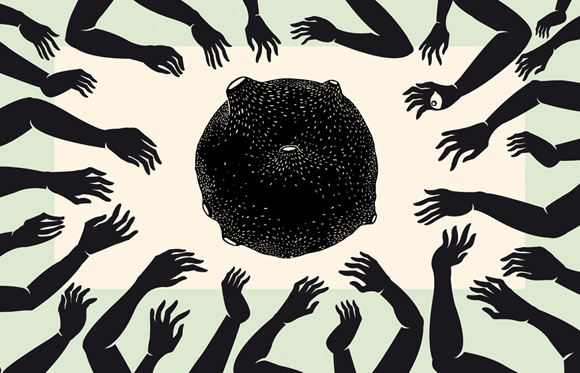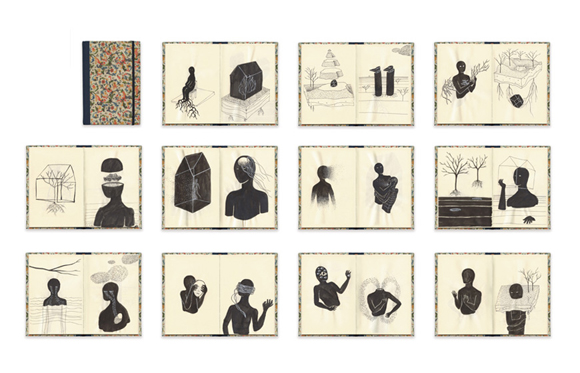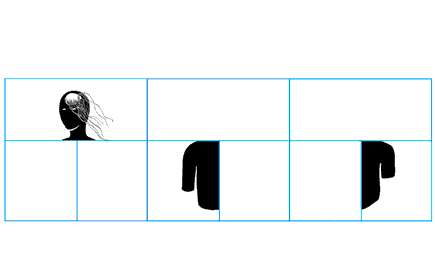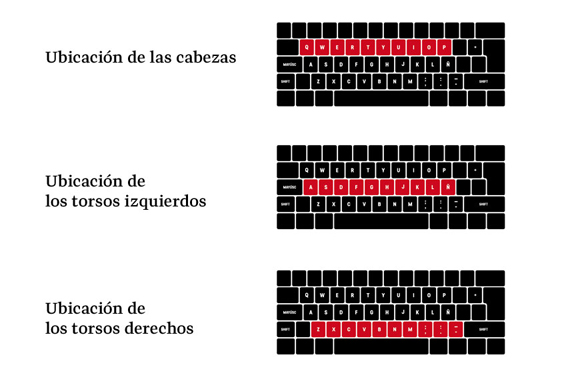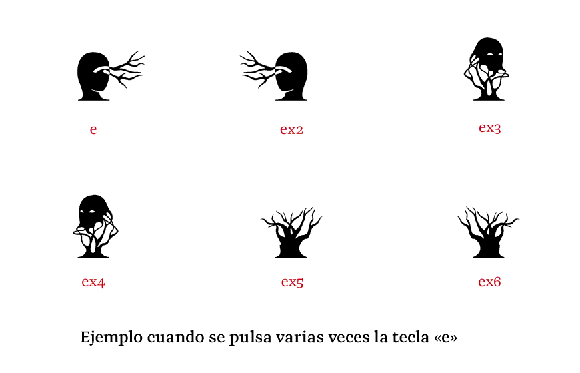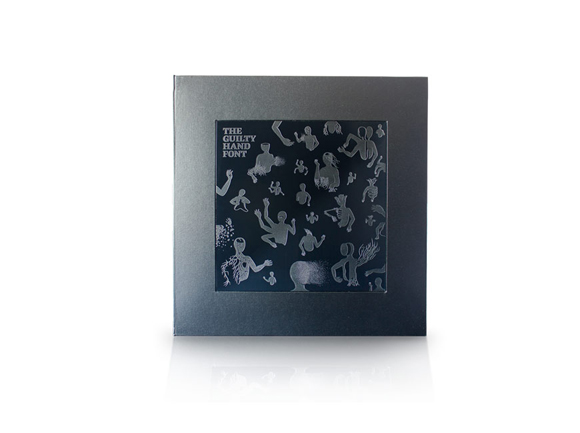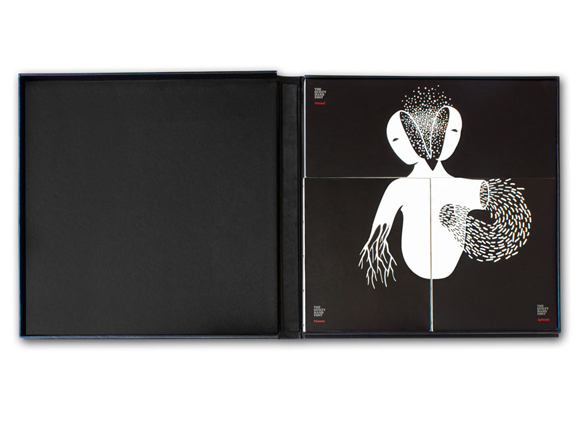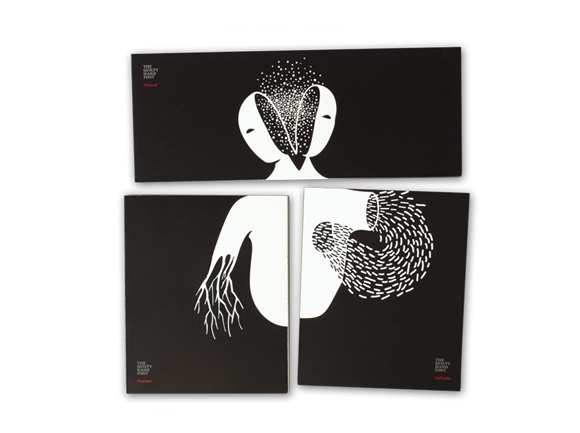
Rubén Chumillas, ha creado la tipo “The guilty hand font” como resultado de su experimentación con el diseño, tipografía e ilustración. Podría tratarse de la primera tipografía que escribe ilustraciones. No estamos hablando de una tipo que tiene dibujos asignados a las teclas, sino de algo mucho más complejo. Como si de un idioma se tratara, The guilty hand font tiene una sintaxis y unas reglas de escritura propias. Los 30 glifos ilustrados se pueden combinar para crear nuevos personajes y con ello escribir 1000 personajes ilustrados diferentes.
¿Cómo surgió el proyecto de The Guilty Hand Font?
El proyecto surgió durante mi último año de estudios en la Escuela Superior de Diseño de Madrid cuando cursaba las asignaturas Tipografía experimental y Producción para artes gráficas. De ambas asignaturas surgió un proyecto editorial común: Un tiempo antes del final, al que posteriormente se sumaron como entidades colaboradoras la Biblioteca Nacional de España, la galería Ivorypress y el Museo della Carta e della Filigrana di Fabriano. Nuestra propuesta debía estar basada en Liber Chronicarum, o Las Crónicas de Núremberg, un incunable de 1493, y la forma en la que cada uno de los alumnos concebíamos el tiempo anterior al final del mundo que conocemos. Tanto José María Ribagorda como Concha García, directores del proyecto y profesores, me animaron a articular mi propuesta en base a mis ilustraciones ya que, desde el punto de vista formal, estarían íntimamente relacionadas con las estampas xilográficas que iluminaban el incunable, más aún si se convertían en tipografía, esto es, en elementos repetibles. El resultado fue una tipografía llamada The Guilty Hand Font Basic compuesta de 30 glifos (10 cabezas, 10 torsos derechos y 10 torsos izquierdos) que permitía crear hasta 1000 combinaciones, 1000 personajes.
¿Como surgieron los personajes ilustrados de la tipografía?
The Guilty Hand comenzaron siendo los cuadernos de esbozo en los que creaba personajes anónimos únicamente con tinta Quink Parker negra y pincel desde hace años. Al principio eran muy toscos pero sus formas fueron evolucionando y mejorando a medida que mi mano fue desarrollando cierta técnica para trazarlos más que por mí capacidad o acción consciente; de ahí su nombre: La mano culpable. Yo no tenía una idea clara del tipo de dibujo que quería obtener. En estos esbozos simplemente trataba de plasmar a través del anonimato y el misterio que genera la tipología de personajes un sentimiento, un estado anímico. Cuando los recopilé y analicé para llevar a cabo el proyecto, me di cuenta de que representan una civilización plagada de monstruos cuyas deformidades y peculiaridades son comunes y expresan carencias o deseos también comunes pero que cada personaje concibe como personales, lo que conlleva la fragmentación de su mundo al estar plagada de subjetividades.
¿Cómo funciona la tipografía?
En lugar de letras o números mi tipografía contiene las cabezas, los torsos izquierdos y los torsos derechos de mis personajes: 344 partes suman en total. De este modo, haciendo combinaciones de tres teclas se puede obtener un gran número de personajes (más de dos millones). La tipografía está programada para que las partes, siendo totalmente independientes, se acoplen perfectamente, pero este es un aspecto que no debe preocupar al usuario pues son detalles técnicos.
Para que su uso resulte sencillo e intuitivo se controla a través de la organización de las partes de los personajes en el teclado. Tanto en el estado de mayúsculas como en el estado de minúsculas, en la fila superior se ubican las cabezas, en la fila intermedia los torsos derechos y en la inferior los torsos izquierdos.
Así, cuando tecleamos de arriba hacia abajo obtenemos un personaje.
Además, si pulsamos varias veces una misma tecla obtenemos alternativas de la cabeza, torso izquierdo o derecho que contiene.
Todas las pautas están recogidas en un manual de uso muy sencillo que indica todos los pasos a tener en cuenta. Primero hacías las ilustraciones a mano y luego las trazabas en Illustrator por necesidades del software que se usa para crear tipografías ¿consideras que fue una ventaja o una desventaja a la hora de crear las ilustraciones? Tras sopesarlo al inicio del proyecto concluí que era el proceso de trabajo más acertado. Laborioso pero acertado: 1 dibujar; 2 escanear; 3 vectorizar los personajes y dividirlos en tres partes (cabeza, torso izquierdo y torso derecho) en Illustrator; 4 finalmente volcar todas las partes ya separadas en el software de diseño de tipografías, donde hacía los ajustes técnicos necesarios y la programación para poder generar el archivo que cualquier persona podría instalar en su ordenador como si se tratara de una Times o una Calibri.
El software de diseño de tipografía es muy preciso y su finalidad es el dibujo de letras, obviamente, con formas sencillas basadas en líneas rectas y curvas muy limpias. No es un programa de dibujo. Mis personajes en cambio podían tener muchos detalles para los que necesitaba ampliar y reducir y no solo eso, también necesitaba manejar varias capas cuando los dividía en partes. En ese sentido, el trabajo previo en Illustrator facilitaba bastante la organización. Lo que sí fue una desventaja a la hora de terminar el proyecto es que como el software de diseño tipográfico está pensado para crear letras, soporta una cantidad limitada de información de dibujo vectorial y me vi obligado a sacrificar 22 partes de los personajes porque contenían muchísimo detalle y el programa no podía exportar el archivo final y se cerraba continuamente. De las 366 partes preparadas, la tipografía contiene 344. Eso fue muy frustrante, sin embargo es bueno llegar a conocer las limitaciones de las herramientas con las que trabajamos para tenerlo en cuenta en futuros proyectos.
¿Que es eso de la metatipografía?
Metatipografía es un término que inventó José María Ribagorda (tipógrafo y profesor en la Escuela Superior de Diseño de Madrid) para nombrar el concepto de tipografía que enseña en sus clases. Parte de la base de que la tipografía no son las letras, lo visible, sino el sistema que permite organizar el espacio y la escritura basado en módulos. Tras asistir a sus reveladoras clases, soy un convencido de que uno de los aspectos menos conocidos, de un modo generalizado, es que la tipografía no tiene porqué ser alfabética ni una simple colección de dingbats. Es cierto que su principal finalidad es la composición de textos de libros, revistas, webs, señalizaciones, etiquetas,… pero no es el único. Entender que las fuentes tipográficas son un pequeño software que podemos programar para que tenga un determinado comportamiento cuando son utilizadas en un editor de texto, da pie a infinitas posibilidades creativas.
¿Qué es lo que fue más difícil a la hora de conceptualizar o ejecutar el proyecto?
Lo más complicado en cualquier trabajo o disciplina creo que es la fase inicial de toma de decisiones. Bajo mi punto de vista es imprescindible dedicar tiempo a la valoración de las diferentes posibilidades hasta que estás seguro de que una de ellas es la más acertada, porque de un planteamiento sólido y bien enfocado siempre saldrá un buen resultado. A partir de ahí el camino está allanado, tan sólo hace falta invertir tiempo, pero en mi caso, el tiempo que requería el proyecto era superior al plazo que tenía. Mi planteamiento era bastante ambicioso: una tipografía experimental y al mismo tiempo un proyecto editorial experimental que la presentara. Eran como dos proyectos finales en uno. Ahora lo pienso y me parece una auténtica locura. Mis noches se confundieron con el día, las tardes con el desayuno, las cenas con las comidas,… Terminé exhausto. Tras la entrega y la evaluación estuve casi dos meses sin dibujar y sin utilizar el editor tipográfico.
¿Te consideras ilustrador o tipógrafo?
Me apasionan los dos campos y coqueteo con ellos, intento aprender todo lo que está a mí alcance, no obstante, creo que ambas profesiones exigen unos conocimientos de los que todavía carezco. Por ello no puedo definirme ni como ilustrador ni como tipógrafo: no sería honesto. De momento prefiero considerarme definirme como diseñador gráfico, como esa persona que está entre dos aguas, lo racional y lo artístico, capaz de aprovechar los conocimientos que posee de varias disciplinas para unirlas en un mismo proyecto reflexionando y organizando: pensando el proceso tal y como me han enseñado los magníficos profesores que he tenido en la Escuela Superior de Diseño de Madrid y en Arte 10.